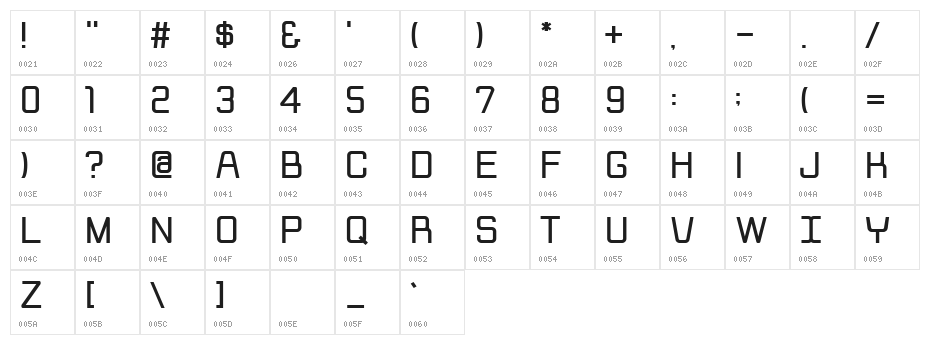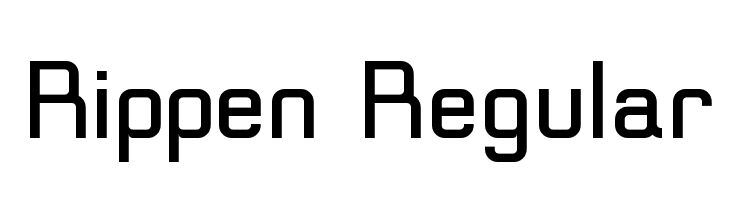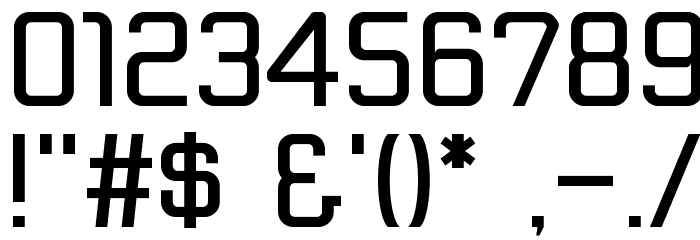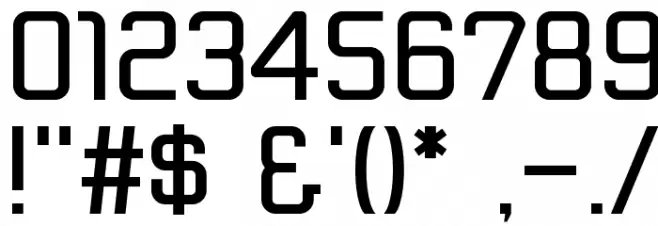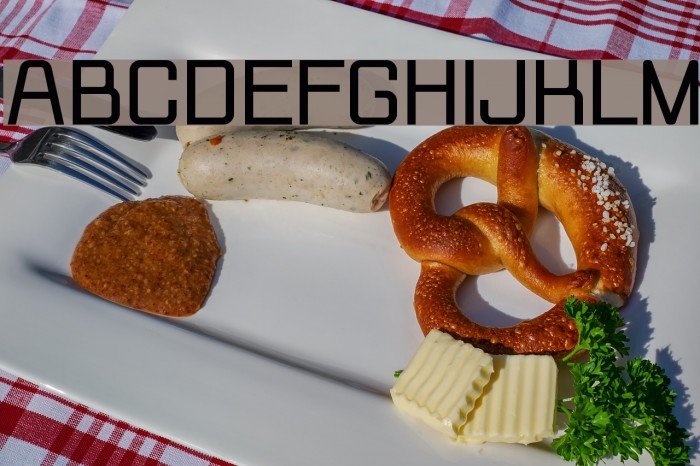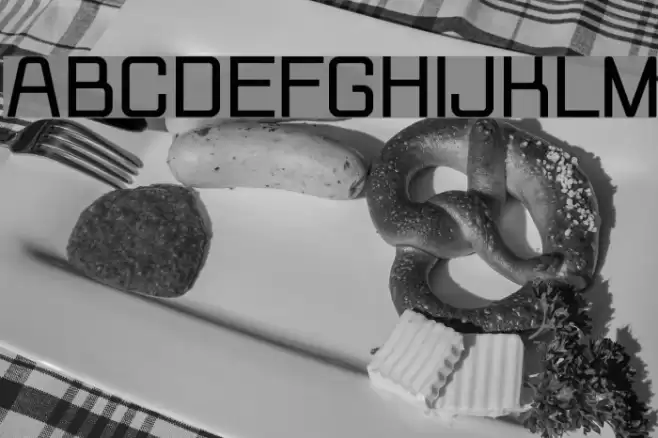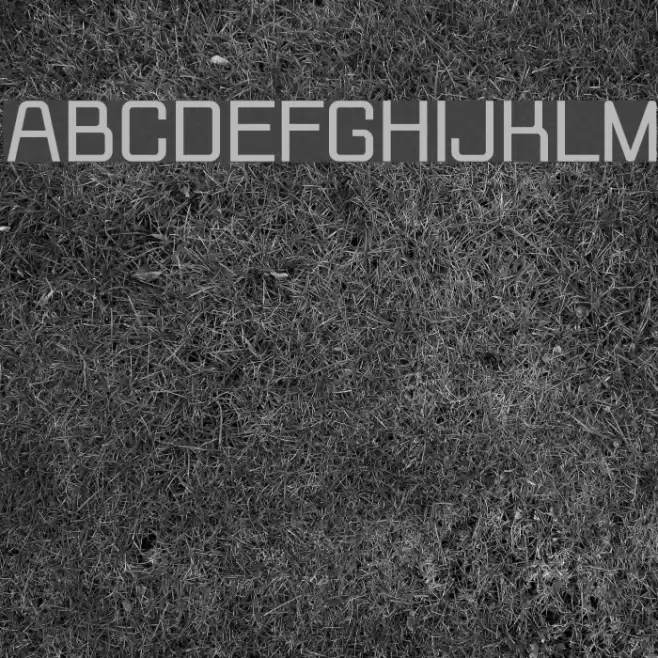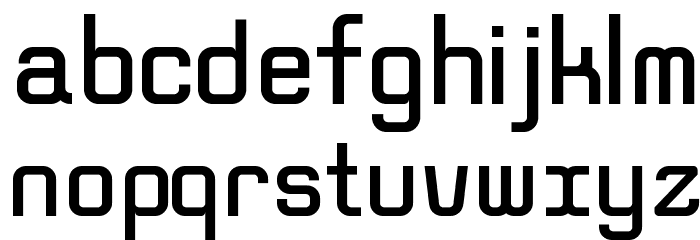
Rippen Regular Font
✎ Thick
| Anwendungsfall | Headlines, Logos, Digital interfaces |
| Vorgeschlagene Projekte | Ideal for branding, digital interfaces, signage, and editorial design where a modern and clean look is desired. |